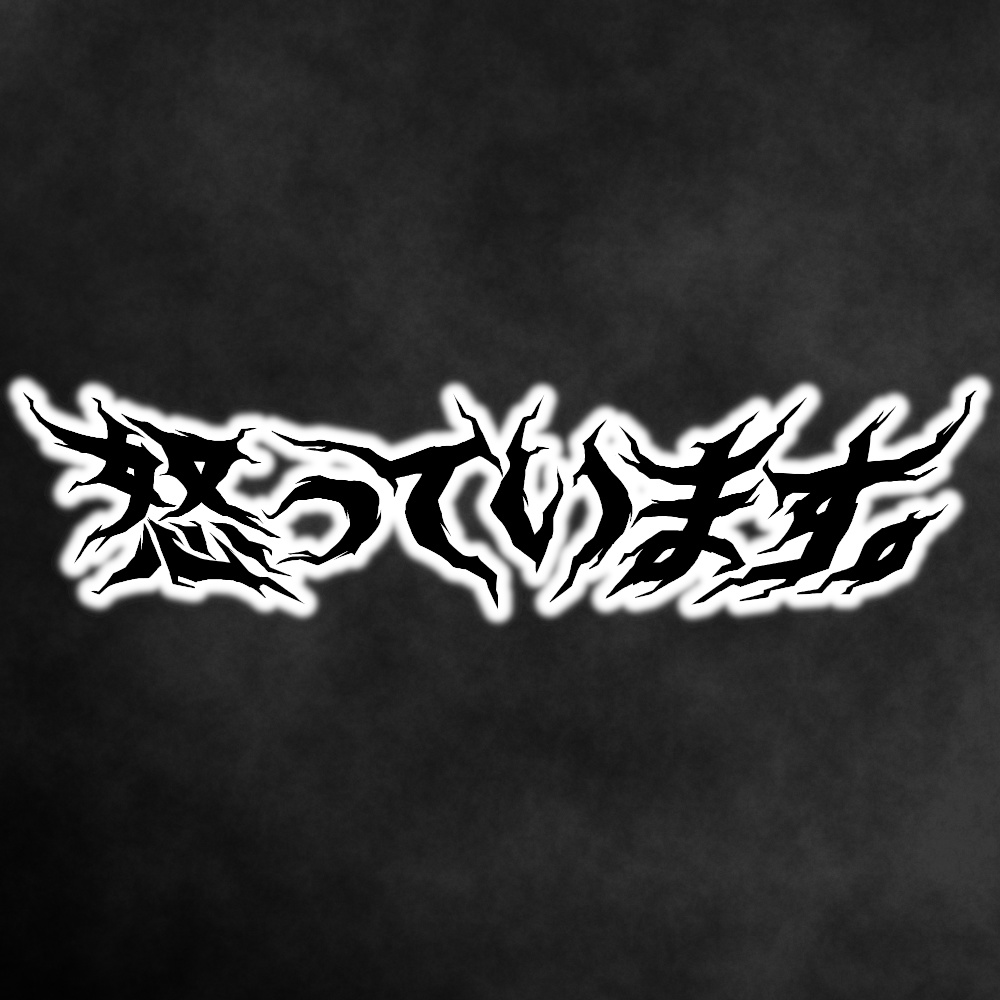
清五郎怒っています.pngDigital500 JPY카트에 담기기프트 보내기About Gift配信・動画・漫画・小説・映像作品・ゲーム・チラシなどでフォントでは表しきれない気持ちを表現したいときに使えるpng画像です。 背景透過png 文字のみ3枚 1913×437 影あり3枚 2000×529 全6枚約束商用・非商用で使用できます。 色・サイズ・比率などの変更は自由です。 本素材をそのまま、または少し変えただけで、配ったり販売するのは禁止です。 犯罪や反社会的行為に使用するのは禁止です。 クレジット表記は不要です。報告も不要です。 使用した場面のスクリーンショット投稿は可能です。 買った人だけで使ってください。清五郎Logos完全初見.png清五郎500 JPYMaterials (Other)雑談.png清五郎500 JPYLogosASMR.png清五郎500 JPYLogos生誕祭.png清五郎500 JPYMaterials (Other)歌枠.png清五郎500 JPYMaterials (Other)いつも応援して下さっている皆様へ.png清五郎500 JPYMaterials (Other)중대발표.png清五郎500 JPYMaterials (Other)IMPORTANT ANNOUNCEMENT.png清五郎500 JPYMaterials (Other)重大発表.png清五郎500 JPYMaterials (Other)ネタバレ禁止.png清五郎500 JPYMaterials (Other)開示請求.png清五郎500 JPYMaterials (Other)大切なお知らせ.png清五郎500 JPYMaterials (Other)ストレス.png清五郎500 JPY더보기